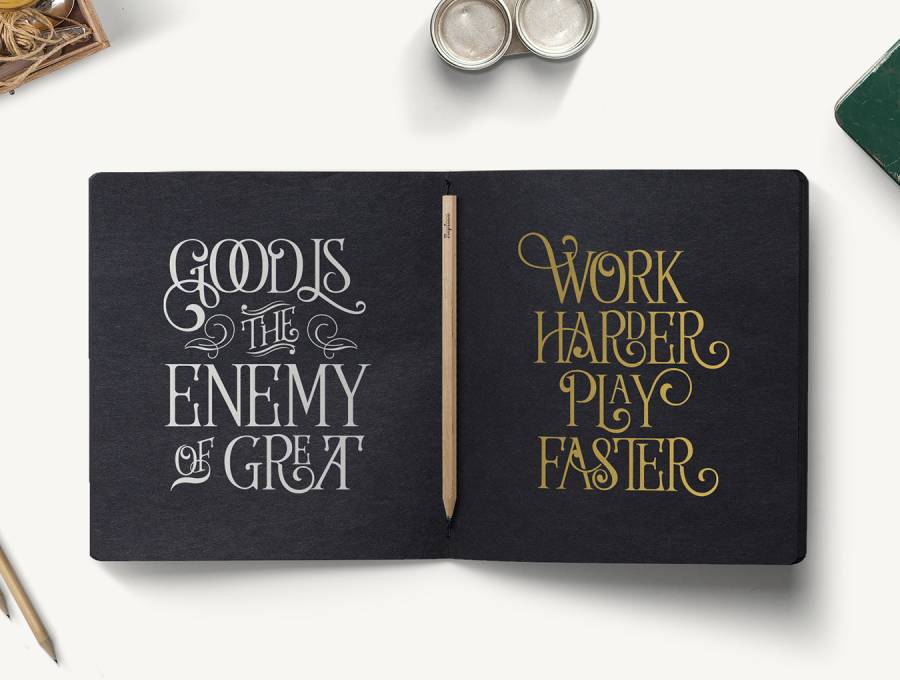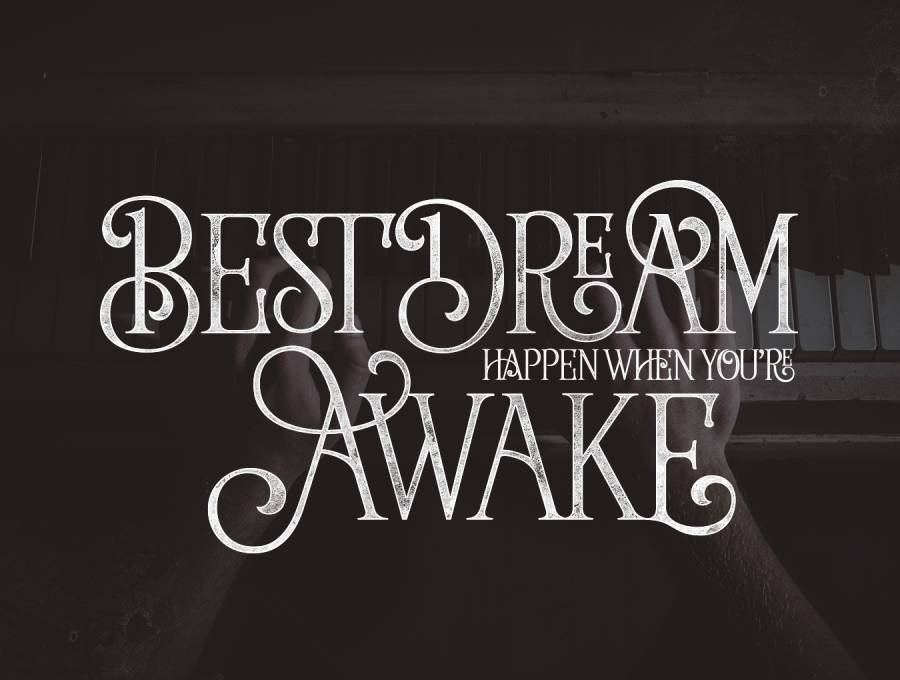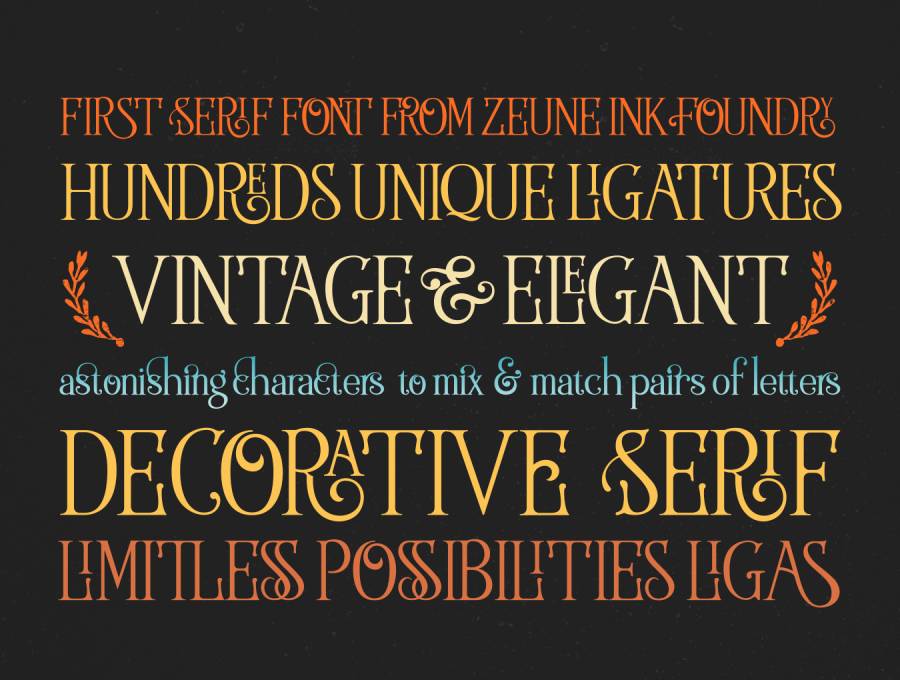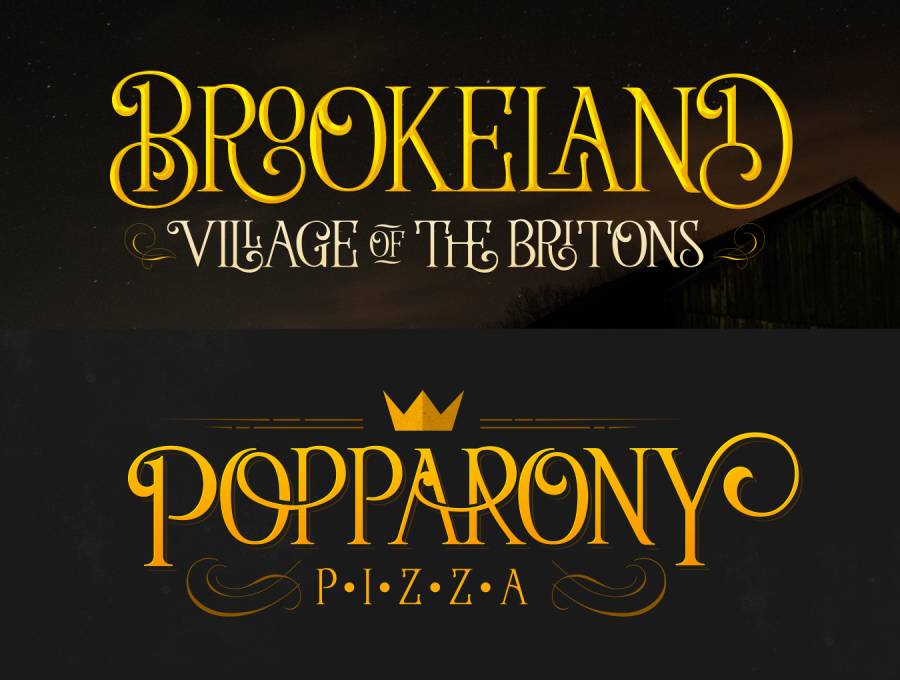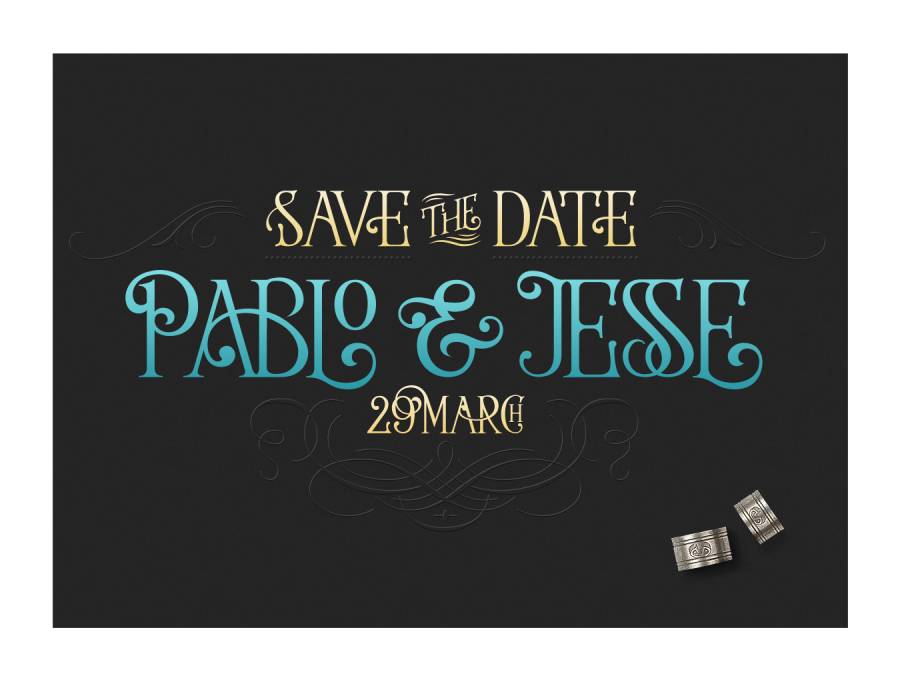
Wallington Pro装饰性衬线复古风格字体
A decorative-serif vintage inspired font, Wallington Pro
Wallington Pro是一种装饰性衬线字体,体现了复古优雅的曲线和功能性结构。所有字形都分为几个OpenType功能,如Ligatures,Contextual alternates,Old Style Numeric和一些令人惊讶的特殊字符,允许您混合和匹配字母对以适合您的设计。
精心设计的爱和易于阅读的字母设计。适用于数字刻字,印刷品,标志,海报,T恤和包装等。